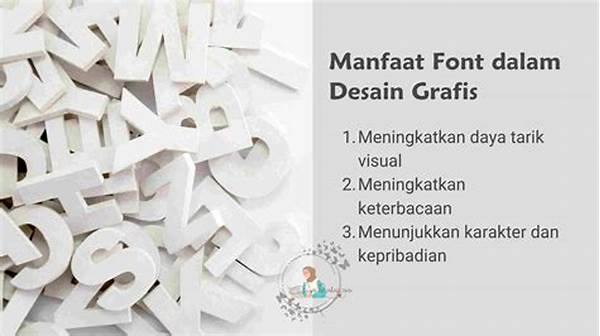
Halo teman-teman! Pernah nggak sih, kalian memikirkan pentingnya font dalam desain? Ternyata, pemilihan jenis huruf bisa mempengaruhi bagaimana merek atau produk kita dipersepsikan oleh orang lain, lho! Jadi, yuk kita bahas lebih dalam tentang dampak font pada identitas visual!
Pentingnya Font dalam Membangun Identitas Visual
Ketika kita berbicara tentang identitas visual, font adalah salah satu elemen yang sering kali terlupakan, padahal punya dampak besar. Bayangkan ketika kamu melihat font yang lembut dan feminin pada merek kosmetik, pasti terbayang sebuah perasaan yang hangat dan ramah. Sebaliknya, font yang tebal dan keras pada produk teknologi menciptakan kesan kuat dan modern. Inilah yang merupakan dampak font pada identitas visual. Pemilihan font yang tepat bisa menyampaikan narasi serta karakter yang kita ingin sampaikan. Lagi pula, font juga bisa mempengaruhi bagaimana audiens mengingat dan mengenali merek kita di antara lautan kompetitor.
Font juga berperan penting dalam menciptakan kesan pertama. Saat audiens pertama kali melihat logo atau materi komunikasi kita, font yang digunakan dapat langsung memberikan gambaran tertentu tentang brand. Misalnya, font sans-serif bisa mencerminkan kesederhanaan dan keandalan, sedangkan font serif mungkin memberikan kesan elegan dan berkelas. Itulah mengapa dampak font pada identitas visual tidak bisa dianggap remeh. Pemilihan font yang tidak tepat bisa membuat pesan yang ingin disampaikan menjadi tidak jelas atau bahkan salah interpretasi.
Dalam praktiknya, memilih font sering kali melibatkan proses trial and error. Tidak jarang, desainer harus menguji berbagai pilihan font untuk menemukan kombinasi yang paling cocok. Pilihan font yang tepat dapat membantu memperkuat identitas merek, sementara yang salah bisa menimbulkan dampak negatif pada keseluruhan identitas visual. Oleh karena itu, penting untuk memberikan perhatian khusus dalam memilih font yang selaras dengan unsur visual lainnya seperti warna dan gambar. Dampak font pada identitas visual adalah salah satu hal krusial yang sebaiknya tidak diabaikan dalam strategi branding.
Bagaimana Font Memengaruhi Persepsi Visual?
1. Menciptakan Emosi: Font dapat memicu emosi tertentu. Dampak font pada identitas visual terlihat ketika huruf tebal digunakan untuk menegaskan kekuatan, sedangkan huruf yang lebih lembut menyampaikan kehangatan.
2. Meningkatkan Daya Ingat: Font yang konsisten dan mudah dibaca memudahkan audiens untuk mengingat merek. Ini adalah salah satu dampak font pada identitas visual yang sering diabaikan.
3. Menjadi Pembeda: Di dunia yang penuh persaingan, font yang tepat dapat membuat merek terlihat unik dan berbeda dari yang lain. Dampak font pada identitas visual membuat brand kita lebih mudah dikenali.
4. Mengomunikasikan Nilai: Pemilihan font juga bisa mencerminkan nilai-nilai yang diusung oleh sebuah brand. Ini adalah aspek penting dalam dampak font pada identitas visual.
5. Menarik Target Audiens: Font harus relevan dengan target pasar. Memilih font yang tidak sesuai bisa menurunkan ketertarikan audiens terhadap merek. Dampak font pada identitas visual selalu berkaitan dengan kebiasaan audiens.
Mengapa Pemilihan Font Penting dalam Branding?
Pemilihan font yang tepat sangat penting dalam branding karena font dapat menciptakan kesan atau menggambarkan kepribadian merek. Bayangkan jika kamu melihat toko buku yang menggunakan font mirip tulisan tangan untuk promosi, dibandingkan dengan font yang lebih formal dan teratur. Pasti kamu langsung merasakan perbedaan atmosfer dan impresi, kan? Itu adalah salah satu bukti bagaimana dampak font pada identitas visual bisa begitu nyata. Font yang dipilih harus merepresentasikan brand secara konsisten di semua media komunikasi, sehingga audiens bisa menangkap pesan yang sama di mana pun mereka berinteraksi dengan merek tersebut.
Selain itu, font juga berperan dalam memberikan kenyamanan visual kepada audiens. Jika font yang digunakan sulit dibaca atau terlalu rumit, bisa-bisa audiens tidak mau meluangkan waktu untuk membaca konten atau materi kita. Di sinilah kita bisa melihat dampak font pada identitas visual. Font yang tidak tepat bisa menghalangi audiens untuk memahami pesan yang ingin disampaikan atau bahkan mengurangi keinginan mereka untuk kembali berinteraksi dengan brand kita. Oleh karena itu, elemen font harus dipertimbangkan secara matang dalam setiap strategi branding.
Tips Memilih Font untuk Identitas Visual
1. Pertimbangkan DNA Brand: Pilihlah font yang sesuai dengan karakteristik dan nilai-nilai merek. Dampak font pada identitas visual akan lebih kuat ketika font mencerminkan DNA brand.
2. Sederhana Lebih Baik: Jangan menggunakan terlalu banyak jenis font. Terlalu banyak variasi dapat menimbulkan kebingungan dan mengurangi dampak font pada identitas visual.
3. Perhatikan Kenyamanan Baca: Pastikan font mudah dibaca di berbagai ukuran dan perangkat. Pengalaman membaca yang baik meningkatkan dampak font pada identitas visual.
4. Konsistensi di Semua Media: Gunakan font yang sama di seluruh platform komunikasi untuk menciptakan identitas yang kohesif. Konsistensi membantu meningkatkan dampak font pada identitas visual.
5. Sesuaikan dengan Target Audiens: Pilih font yang sesuai dengan selera dan kebiasaan target pasar. Jika tidak, bisa-bisa dampak font pada identitas visual terabaikan.
6. Uji Coba Font: Sebelum memilih, coba font dalam berbagai konteks untuk melihat dampaknya. Ini membantu menilai dampak font pada identitas visual lebih akurat.
Mari kita jadikan pemilihan font sebagai prioritas dalam strategi branding. Dampak font pada identitas visual sangat signifikan dalam membangun hubungan emosional dengan audiens. Sama seperti warna dan elemen desain lainnya, font juga boleh menjadi alat komunikasi yang efektif. Penting bagi kita untuk melakukan penelitian dan bereksperimen dengan berbagai font untuk menemukan yang paling cocok merepresentasikan karakter brand. Dengan begitu, kita bisa menciptakan identitas yang kuat dan tak terlupakan.